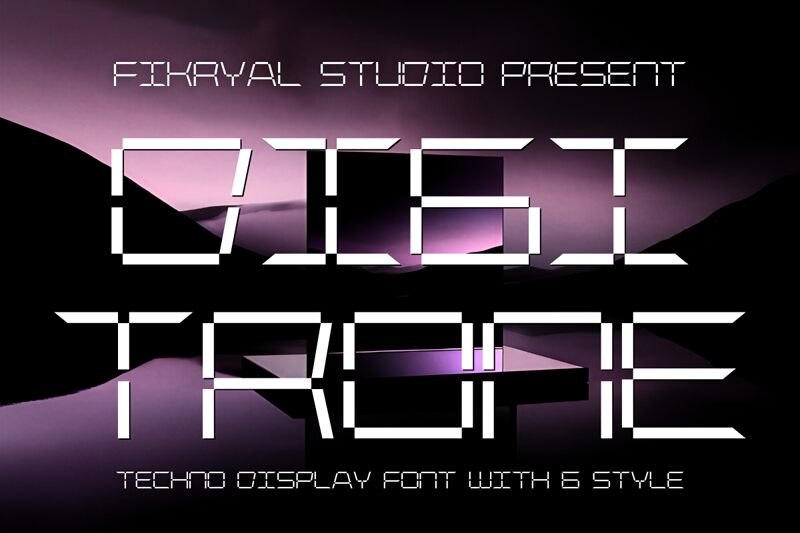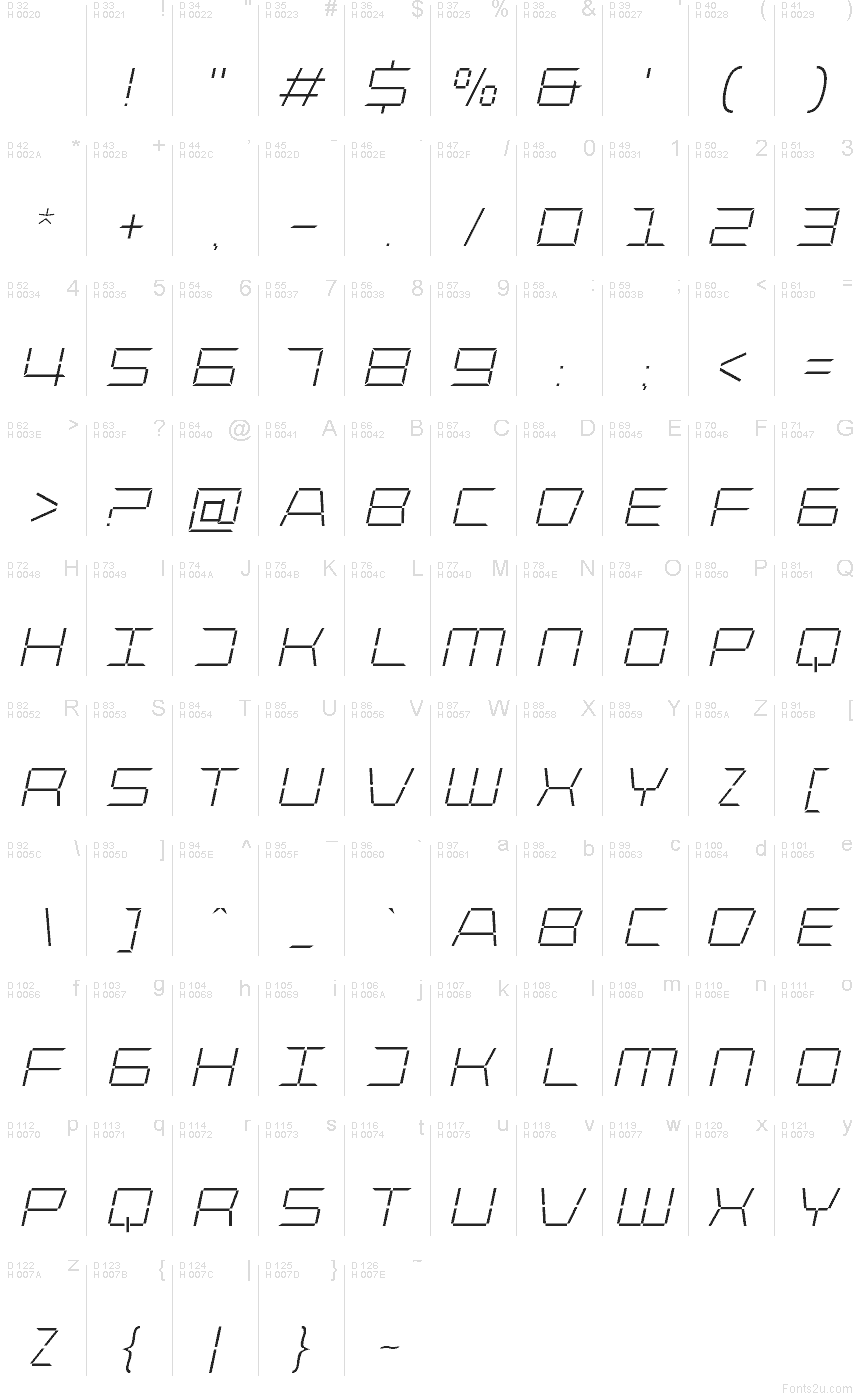
Digitrone Light Italic od Fikryal Studio je bezplatné digitální displayové písmo se zkoseným, segmentovaným vzhledem elektronických informačních tabulí. Jeho mimořádně tenké tahy, široké proporce a ostré zlomy dodávají písmenům čistý technický profil, přičemž otevřené mezery nahrazují řadu běžných spojů.
Digitální grafika je pro něj nejpřirozenějším prostředím, zejména nadpisy rozhraní a branding technologických značek, které těží z futuristického ladění. Hodí se také pro hudební grafiku a plakáty na akce s kybernetickou nebo arkádovou tematikou. Opakující se segmentové zářezy mohou evokovat ukazatele na přístrojových deskách, grafiku plošných spojů a motivy inspirované stroji.